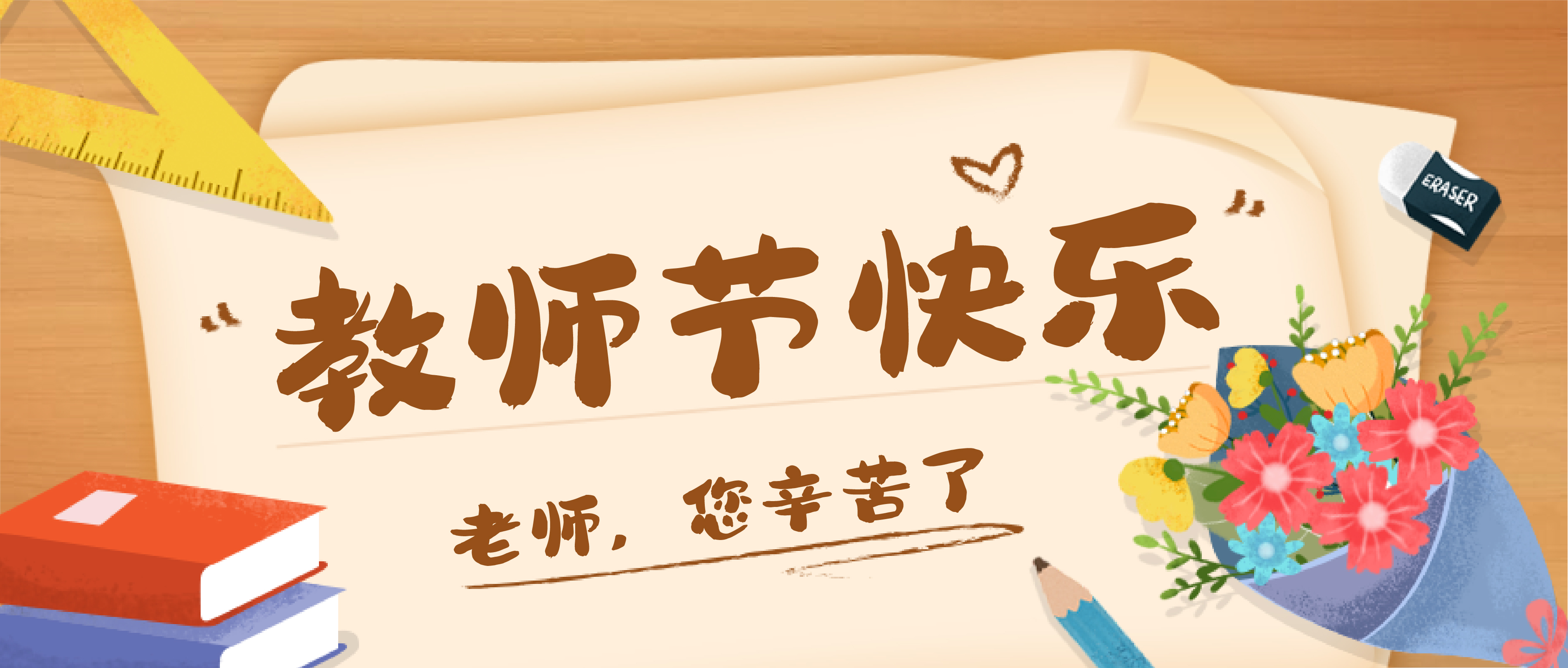
兵克笨笨体
兵克笨笨体,兵克笨笨体,旨在创造一种可爱、圆润、活泼且充满生气的字体风格。摒弃了传统字体中的尖角和折痕,采用大量圆润的线条勾勒,使得整个字体看起来更加柔和、亲切。同时不拘泥于笔画的绝对规整,而是追求随性洒脱的感觉,从而赋予字体更多的生命力和活力。适用于标志设计、包装设计、海报设计、广告、招牌、漫画、游戏、儿童读物等视觉场景。